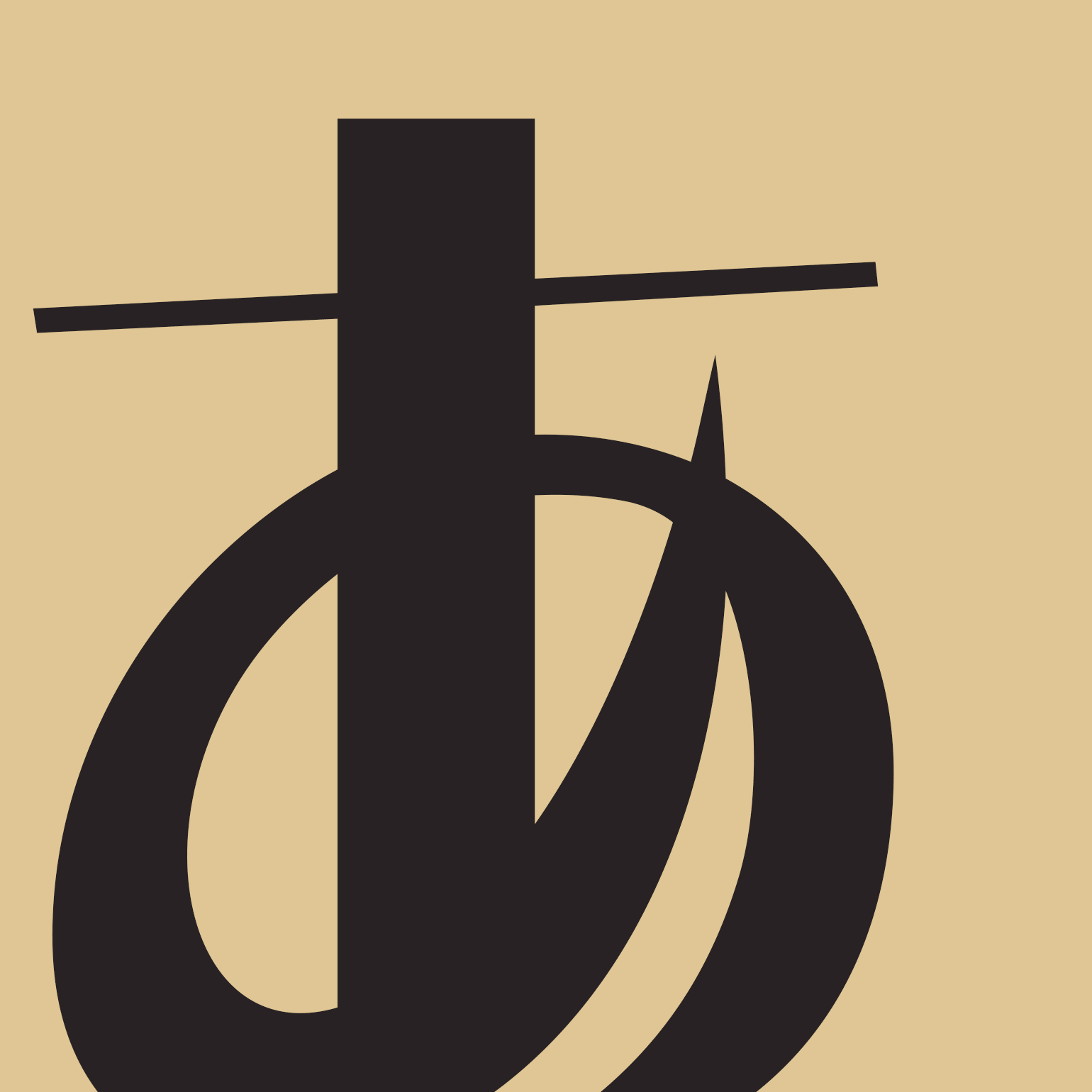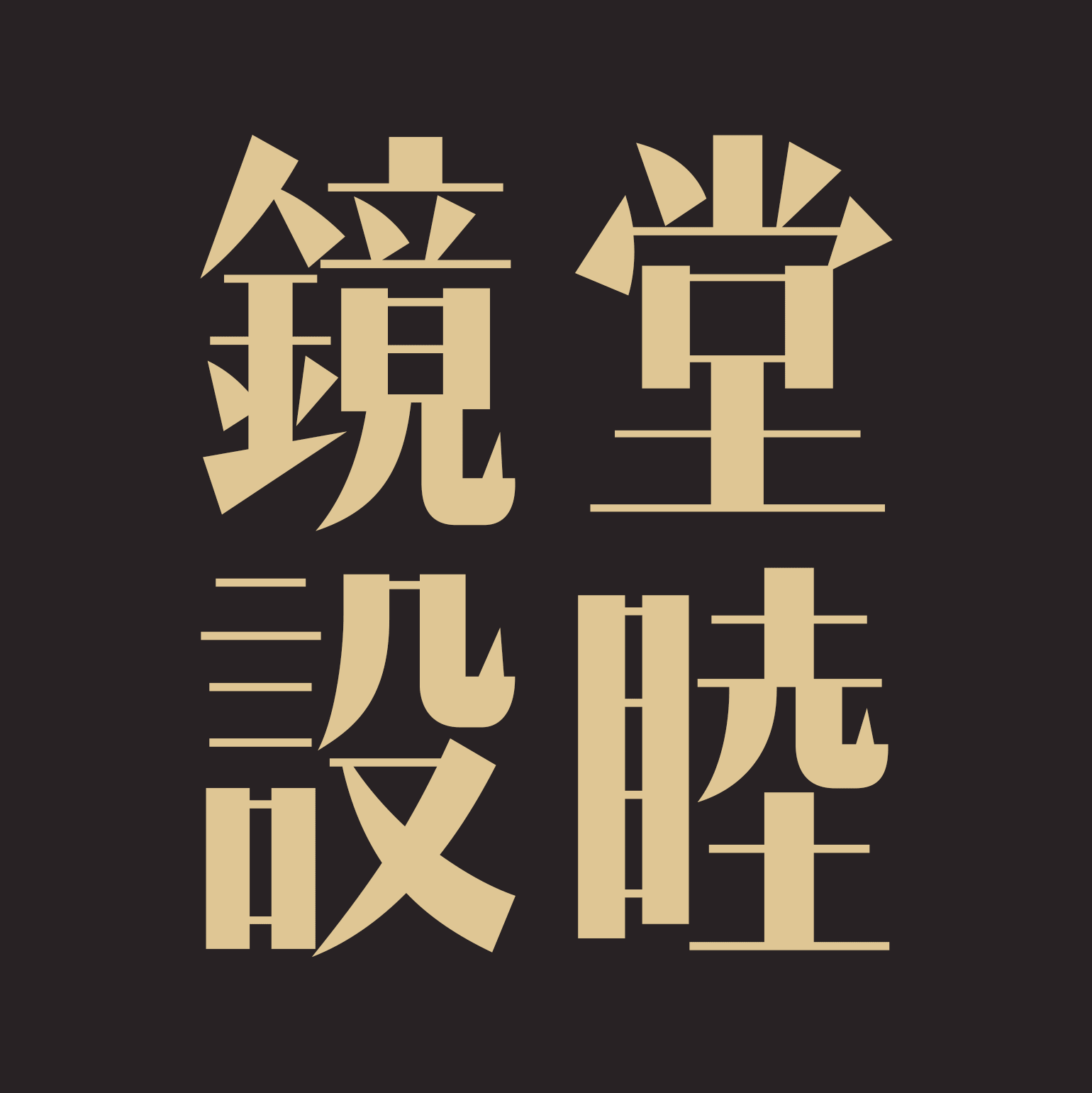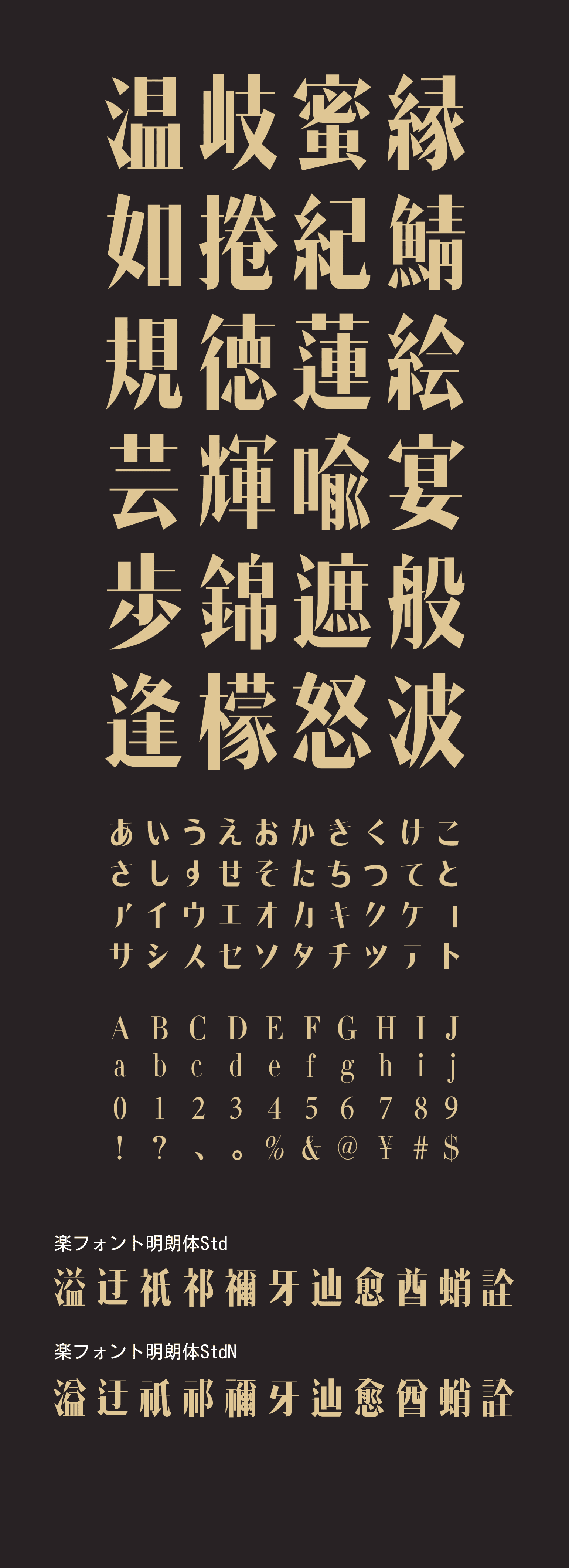
明朗体(めいろうたい)
1950~1960年代の宣伝スローガンや広報ポスターなどに見られる手書き文字を原点に、現代的な設計とニーズを組み合わせリデザインされた、懐かしくも新しい書体です。 筆を勢いよく抜いたようなエッジの効いたハライの表現と、力強く墨溜まりを作ったトメの表現が、力強くシャープなイメージを与えます。 緩急のある線幅で文字に躍動感を持たせつつも、やや細めの字面を保つことで、バランスの良い文字組みを実現。 しっかりした重厚感の中にも、気楽でリズミカルな軽さを失わない。 楽フォントが実現した、この独特の存在感は、タイトルや見出しなどに魅力を発揮します。